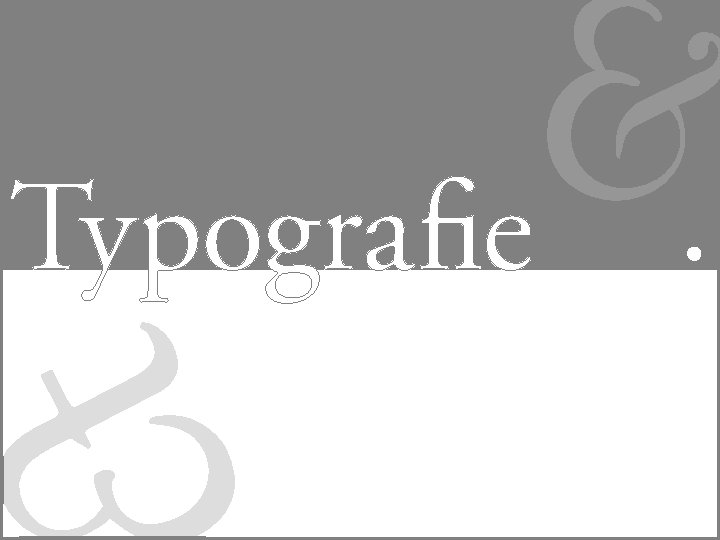
Úvod
Co je typografie? Z řečtiny, název původně používaný pro knihtisk, přípravu knihtisku z typů, liter. V širším pojetí nauka o tvorbě vzhledu produktů tiskové výroby (knihy, časopisy, noviny, plakáty apod. ). Typografie je věda o písmu. Zabývá se způsoby psaní, editace a sazby dokumentu. Typografie je obor lidské činnosti zabývající se tím, jak má dokument vypadat, aby byl dobře čitelný a přehledný a přitom působil esteticky. 5
Proč se typografií zabývat? • pravidla vznikala během staletí přirozeným výběrem • jako pravidla jsou použity postupy vedoucí k nejlépe čitelným a přehledným výsledkům • mnohá pravidla souvisejí s gramatickými pravidly daného jazyka (pravidla českého pravopisu) ― mnohdy je těžké rozlišit, co je pravidlem typografickým a co pravopisným • dokumenty dnes vytváří každý 6
Základní pojmy
Typografické měrné soustavy 8 Systém Didotův Systém pica [pajka] vychází z pařížské stopy = 32, 48 cm vychází z angloamerické stopy = 30, 47 cm 1 m = 2660 bodů 1 cicero = 12 bodů 1 bod ≈ 0, 3759 mm 1" = 72 points (72, 27) 1 pica = 12 points 1 point ≈ 0, 3528 mm 12 b, (12 ), 1 c, (1 cc) 12 b, (12 pt), 1 p (1 pc) viz strana 261– 262
Písmo
Abeceda 10
Dělení písem [1] 11
Dělení písem [2]
Dělení písem [3] 13
Rodina písma 14
Kombinace písem • kombinace podobných písem • kombinace písem z různých dob vzniku (renesanční × moderní) • nestejná střední výška písma a výška verzálek 15 • kombinace výrazně rozdílných písem • kombinace písem z odpovídajících dob vzniku • co nejpodobnější střední výška písma a výška verzálek
Glyfy • standardní ligatury (slitky) • volitelné ligatury (slitky) • zlomky • indexy • kapitálky • minuskové číslice • ornamenty 16 viz strana 232– 234
Ligatury (slitky) 17 viz strana 228– 232
Vývoj ampersandu 18
Vyrovnání párů (kerning) 19 viz strana 219– 225